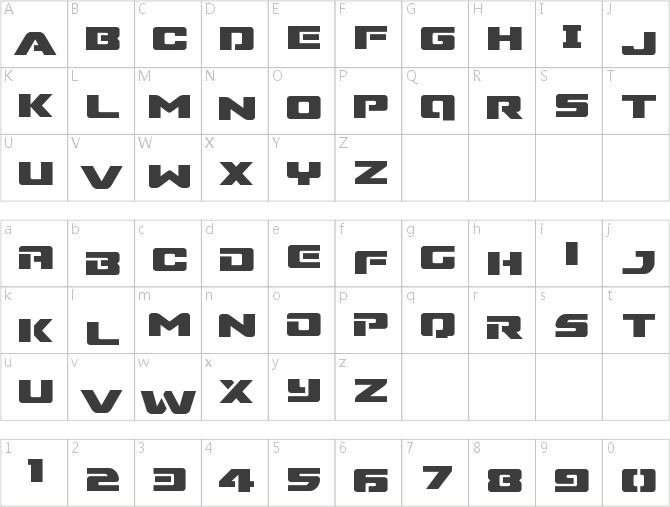
Super Commando Expanded
Super Commando Expanded介紹
Super Commando Expanded字體字庫是一款讓人賞心悅目、百看不厭的英文字體,適合各類廣告和產品包裝設計應用,字體大小0.03MB,格式為ttf字體,上傳用戶是afig,作者/版權方為未知